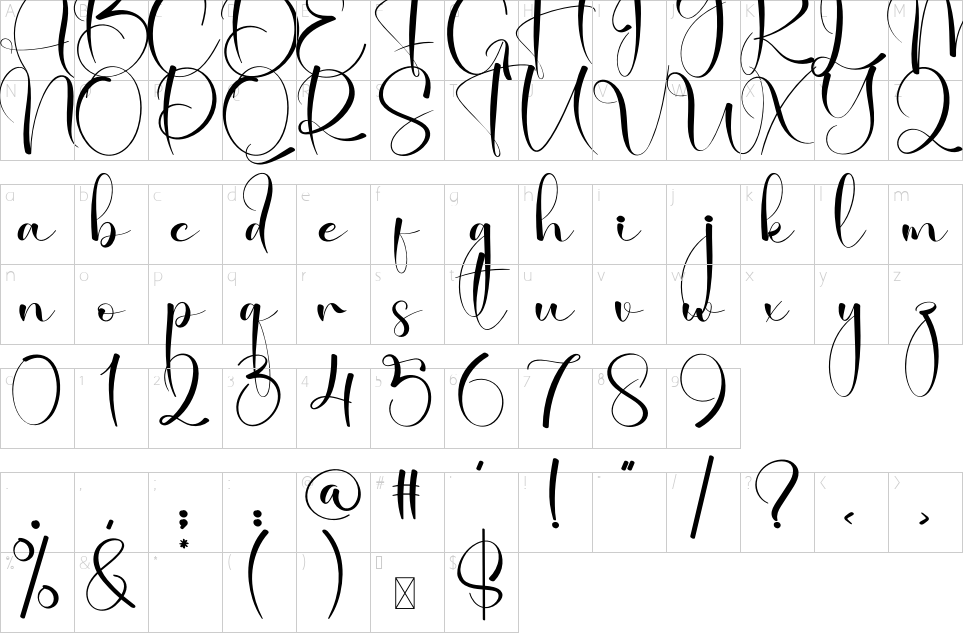
A fonte ‘Grandma Font’ é uma opção versátil e encantadora para designers e criadores de conteúdo que procuram uma mão cheia de características levemente vintage e confortável para títulos e textos menores. Desenvolvida por scratchones, esta font é um dos arquivos gratuitos da categoria Fontes Grátis, disponível tanto para Windows quanto para Mac. Com mais de 779 downloads desde sua criação, é evidente que a família de designers e criadores aprecia o estilo único e versátil desta font, que se adapta perfeitamente ao seu uso em diversos projetos digitais. Se você está buscando uma fonte elegante para personalizar seu próximo design gráfico ou site, a ‘Grandma Font’ é um ótimo lugar para começar.